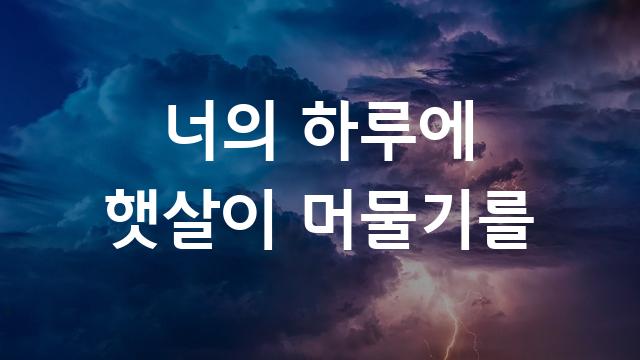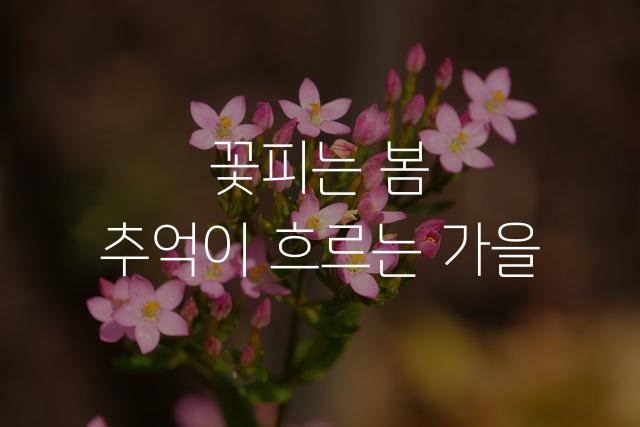
고양체는 고양시청에서 제작한 각진 손글씨 스타일의 한국어 폰트입니다. 이 폰트는 독특한 각진 디자인과 개성적인 터치로 메시지에 생동감을 더합니다.
고양체은(는)
손글씨, 네모꼴, 감성적인, 단단함 계열의 생김새를 가지고 있으며
어린이 책, 카페 메뉴, 소셜 미디어 등에서 자주 활용되며, 효과적인 메시지 전달에 적합합니다.
이 폰트는 교육, 라이프스타일, 유아/가족 분야에 잘 어울리며,
친근한, 귀여운, 편안한 느낌을 담고 있는 것이 특징입니다.